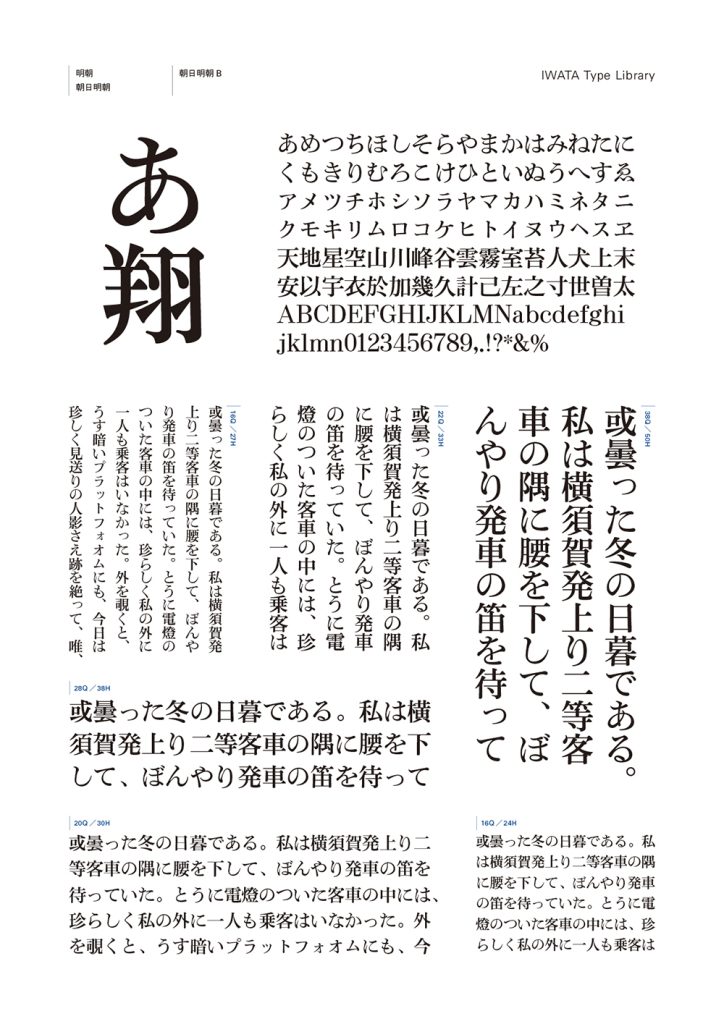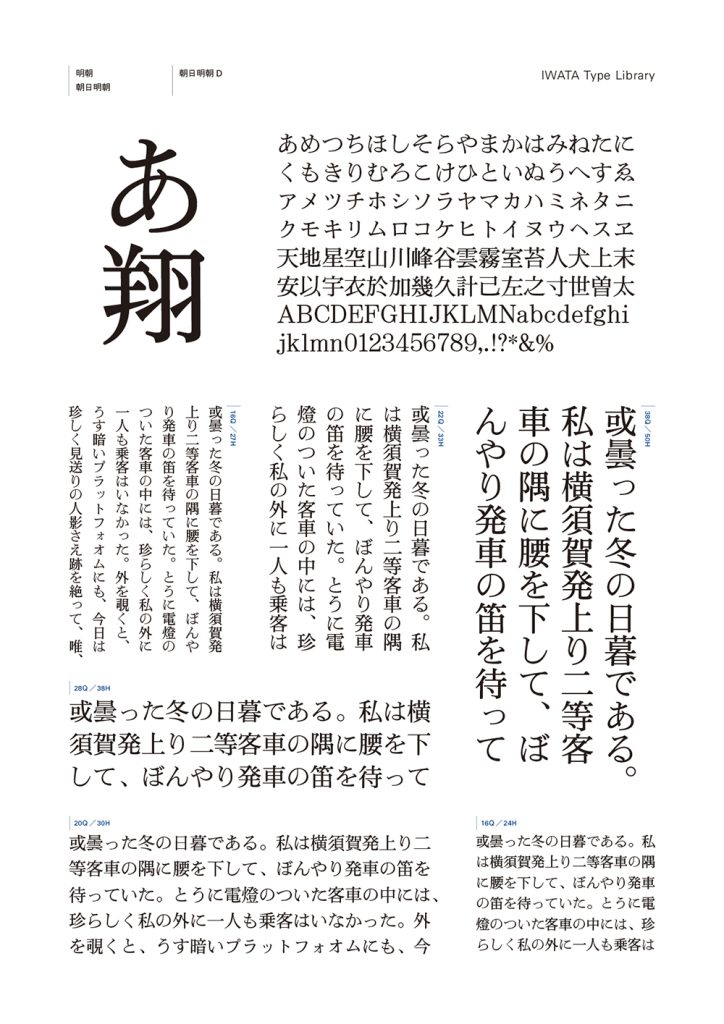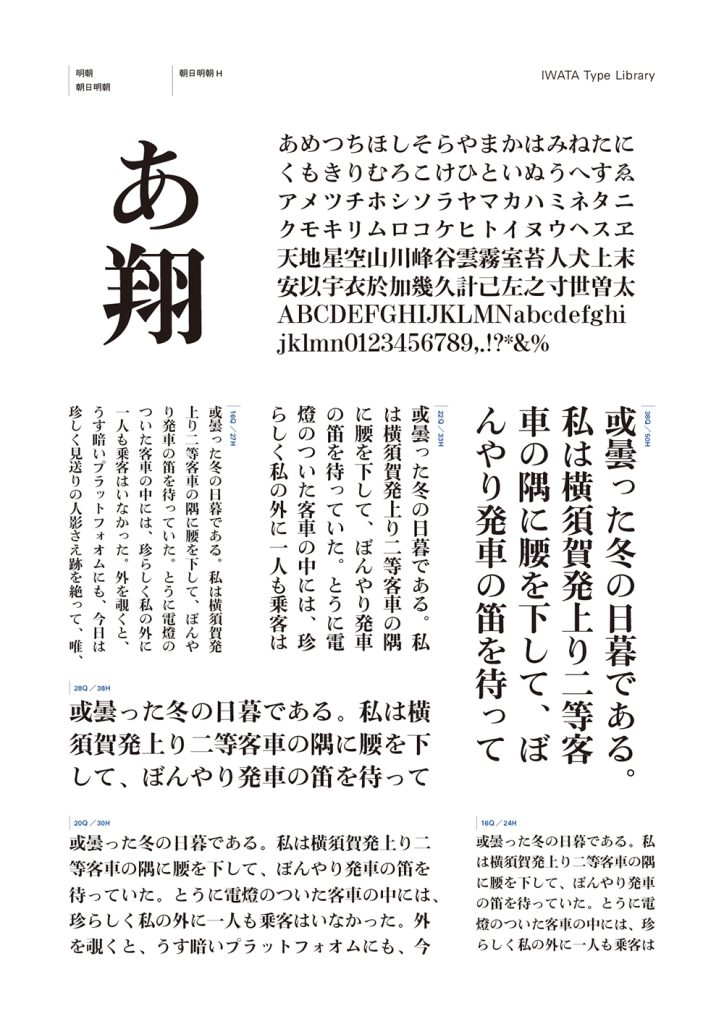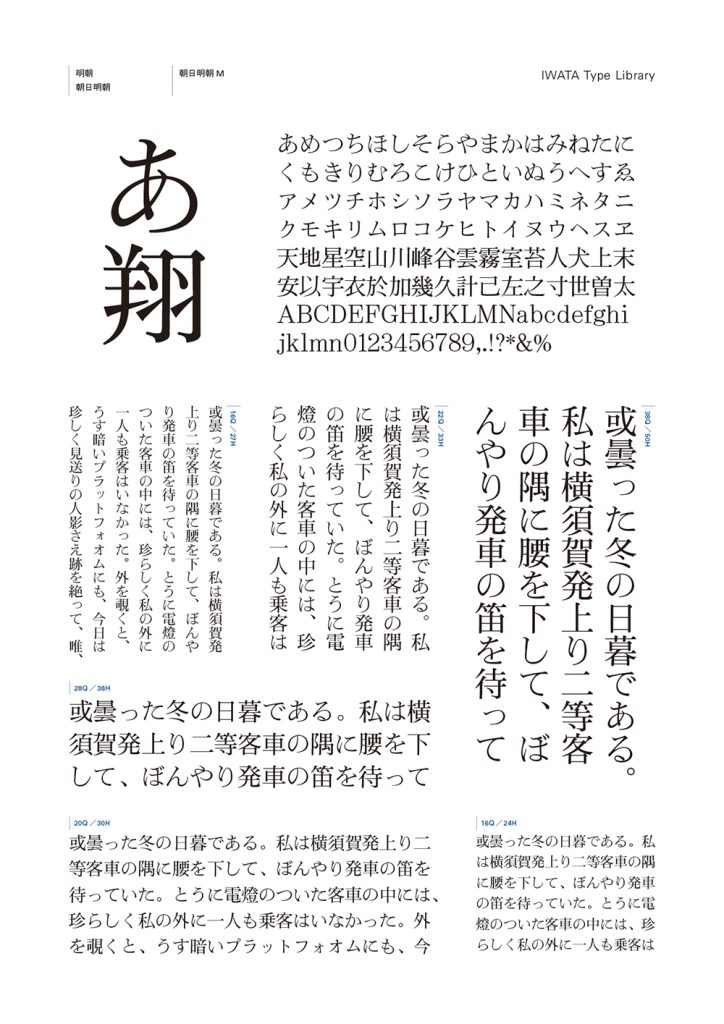
筆の自然な流れを生かしたかなと、広めのふところによる安定感のある、優雅さと柔軟性を兼ね備えた「凜」とした佇まいが特徴の明朝体です。
朝日新聞の活字時代から受け継がれ、視認性を高めるために線幅を調整しながら進化している、伝統と新しさを併せ持つ書体です。
新聞以外にも、多様な媒体で活用できる汎用性の高さも魅力です。